Як вибрати правильний шрифт для сайту і статті
Шрифт - це важливо. Як повітря, який не помічаєш, поки все в порядку. Більшість людей поняття не мають, як називаються шрифти і чим вони різняться (і це нормально), але безпомилково відчувають, що з вашим сайтом щось не те, якщо шрифт, який ви використовуєте, не підходить вашому проекту.
Що таке насиченість шрифту
Насиченість шрифту (накреслення, font weight) визначає товщину кожної літери. Зазвичай ми звикли називати текст нормальним (normal) і жирним (bold). У шрифтів можуть бути так само додаткові варіанти товщини - від дуже тонких (super light) до дуже жирних (super bold).
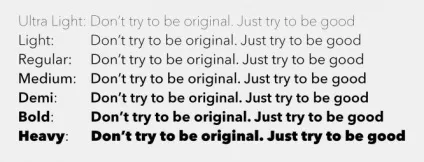
Яким повинен бути розмір шрифту на сайті
Налаштування параметрів шрифту для різних типів проекту
Ми розглянемо 4 варіанти поєднань різної насиченості шрифту в заголовках і в тексті. Вони допоможуть висловити тональність сайту, щоб він виглядав гармонійно і у вас вийде хороший проект.
1. Жирний заголовок і нормальний текст
Це саме базове поєднання, яке буде добре працювати в більшості випадків. Використовуйте, якщо ваше завдання зробити просто хороший сайт без яскраво вираженого акценту.
Для яких сайтів підійде: для будь-яких.
Приклад: Сторінка вакансії. У прикладі використовуються шрифти: Open Sans (для заголовків) і Roboto (для тексту).
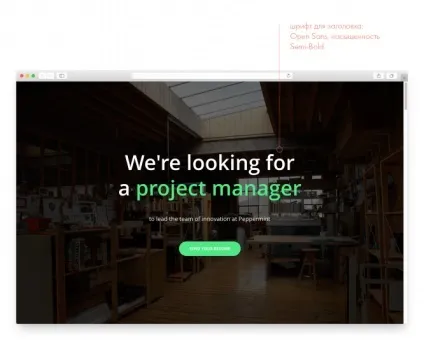
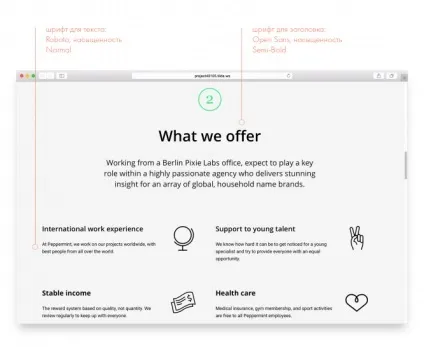
2. Жирний заголовок і нормальний текст
Для яких сайтів підійде: бар, коворкінг, анонс концерту, спортивні змагання, промостраніца туру і т.д.
Приклад: Сайт коворкінгу. У прикладі використовуються шрифти: Ubuntu (для заголовків) і PT Sans (для тексту).
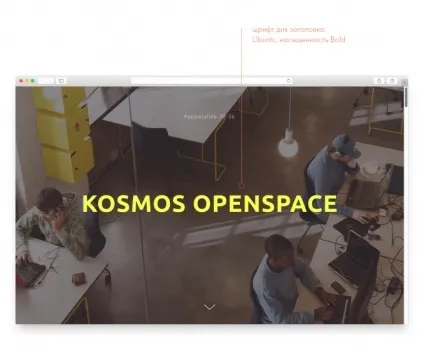
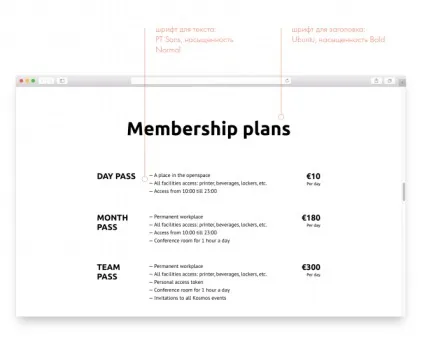
3. Жирний заголовок і тонкий текст
Більш незвичайне поєднання, виглядає ефектно за рахунок контрасту. Доречно в разі, коли вам потрібно поєднувати і драйв, і стиль
Для яких сайтів підійде: Наприклад, таке поєднання ми використовували на Лендінгем нашого курсу «Інтернет-маркетинг з нуля». З одного боку, нам потрібні були яскраві, добре Новомосковскемие заголовки, з іншого боку, текст повинен був передати естетику якісного оформлення курсу.
Приклад: Сторінка дизайн-студії. У прикладі використовуються шрифти: Noto Sans (для заголовків) і Open Sans (для тексту).
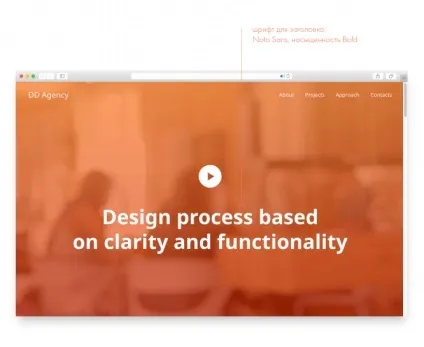
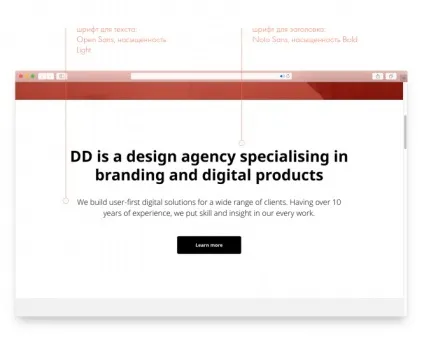
4. Тонкий заголовок і тонкий текст
Поєднання для проектів, пов'язаних з високими технологіями, чимось прогресивним і сучасним. Або естетичним і стильним. Особливо добре спрацює, якщо у вас багато білого простору і є невеликі акценти яскравих кольорів. І красиві фотографії.
Для яких сайтів підійде: технологічні пристрої, ювелірні прикраси, дороге кафе або ресторан, студія краси.
Приклад: Лендінг мобільного застосування для обробки фотографій.
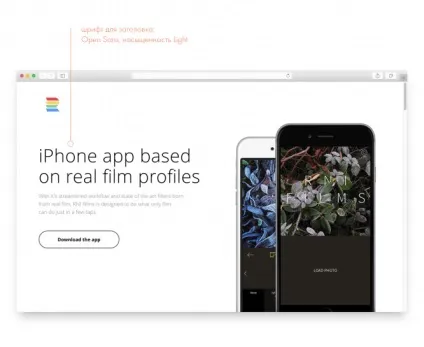
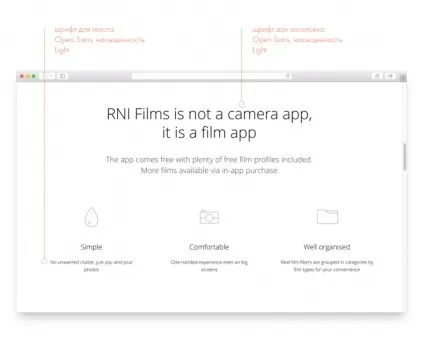
Приклади поєднань різних шрифтів
Поєднуючи різні шрифти в заголовках і в тексті, можна домогтися різного ефекту, висловити характер і тональність сайту.
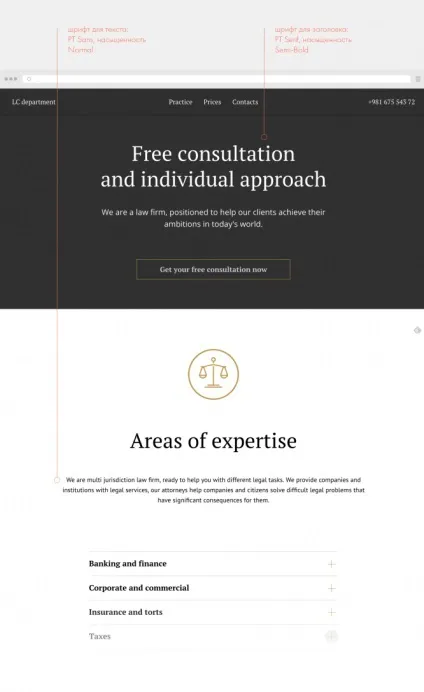
Підбираємо шрифти для статті
У статті найголовніше, щоб текст Новомосковсклся максимально легко. Тому він повинен бути контрастним і не дуже великим.
Приклад: Сторінка поста в блозі про моду.
Приклад: Корпоративний блог.
З зарубками або без?
Довгий час вважалося, що шрифт із зарубками краще Новомосковскется, так як зарубки утворюють направляючу лінію і погляду зручніше і швидше ковзати уздовж неї. З появою перших комп'ютерів стали поширені шрифти без зарубок, так як на екранах з низьким дозволом більш розбірливо виглядали шрифти простої форми, без зарубок.
Сучасні дисплеї однаково добре відображають і ті, і інші. Тому зараз вибір «із зарубками або без» - питання характеру повідомлення, а не Новомосковскбельності. Шрифти із зарубками можуть задавати більш формальний тон і бути придатними для деяких брендів.
Список хороших шрифтів, в яких є кирилиця
читабельність шрифту
Стиль, який застосовується таким чином, поверх загальних параметрів, завжди буде пріоритетним. Тому, якщо раптом ви міняєте параметри в налаштуваннях сайту, а зміни не видно, значить в цьому місці застосований «інлайновий стиль». Щоб його прибрати, потрібно виділити текст і натиснути іконку «очистити».
Приклад 1: Текст Новомосковскется не надто
Приклад 2: Текст Новомосковскется добре
Якщо тема вибору шрифту вам цікава, знайдіть хороші сайти, близькі до вашого проекту, і подивіться які шрифти вони використовують. Визначити це допоможе розширення для браузера What Font.